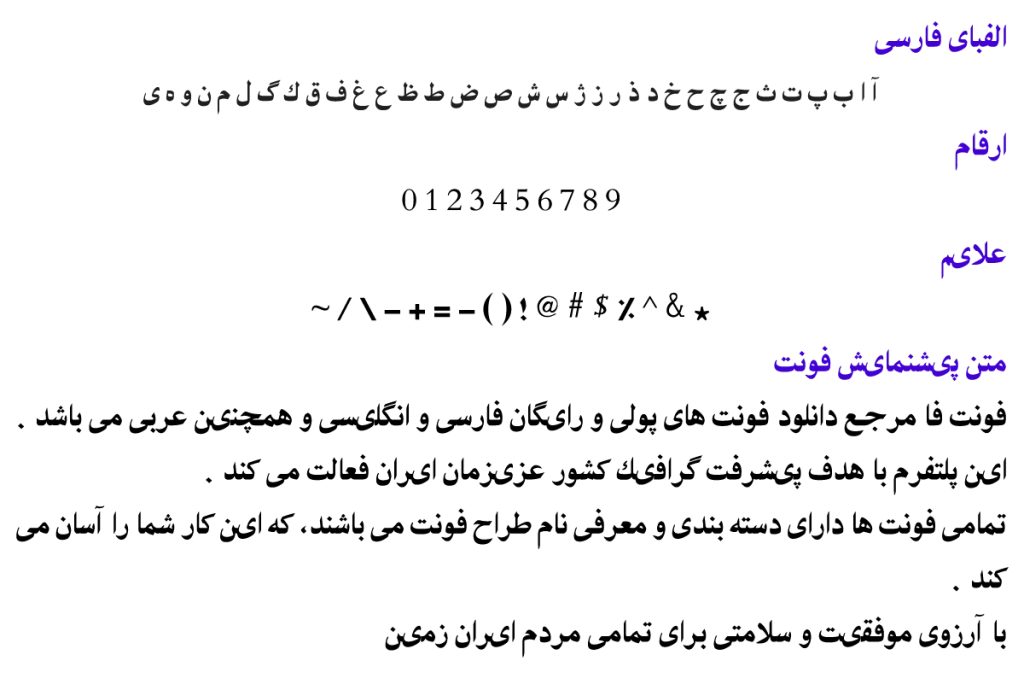
فونت فارسی نسخ تیتر – Mj Naskh Titr
طراح فونت: مجتبی کیا نوع فونت: فونت خوشنویسی و فونت عنوان
توضیحات و معرفی فونت نسخ تیتر
فونت فارسی نسخ تیتر ( Mj Naskh Titr ) از مجموعه فونت های سری Mj می باشد، و نیز نوع فونت خوشنویسی و عنوان می باشد.
فونت خوشگل مربوط توسط مجتبی کیا در سال 1390 طراحی و ساخته شده است.
و نیز فونت Mj Naskh Titr در 3 وزن معمولی و توخالی خطی و سایه است.
- Mj Naskh Titr Regular
- Mj Naskh Titr Outline
- Mj Naskh Titr Shadow
در عکس زیر، شعر دل نشین وطن که با این تایپفیس طراحی شده، به نمایش درآمده است.